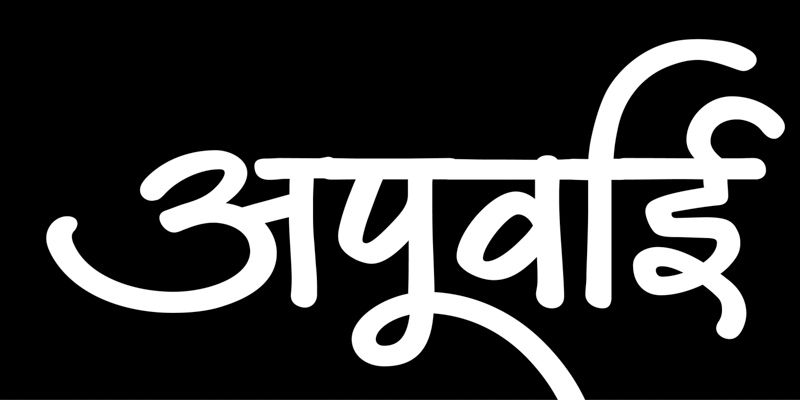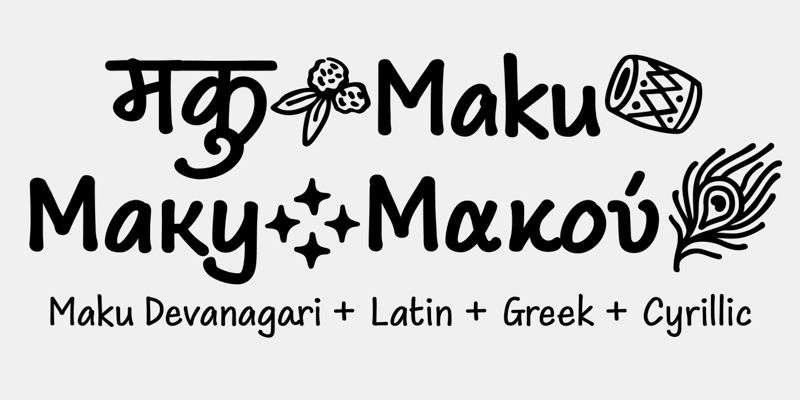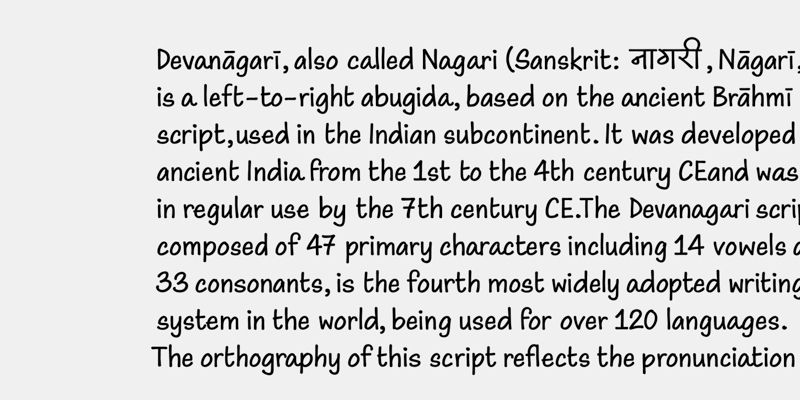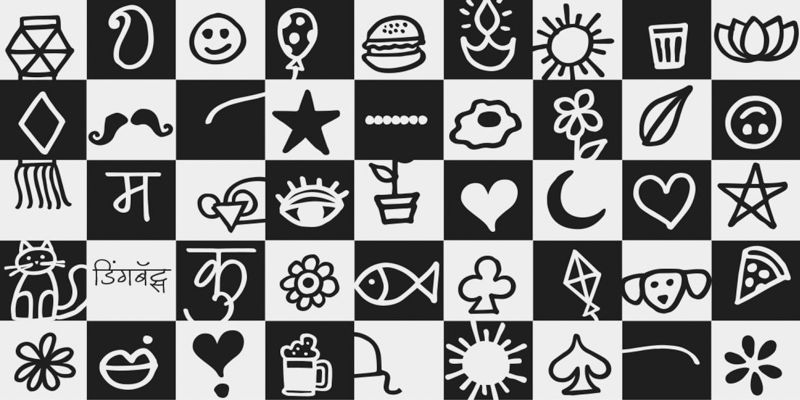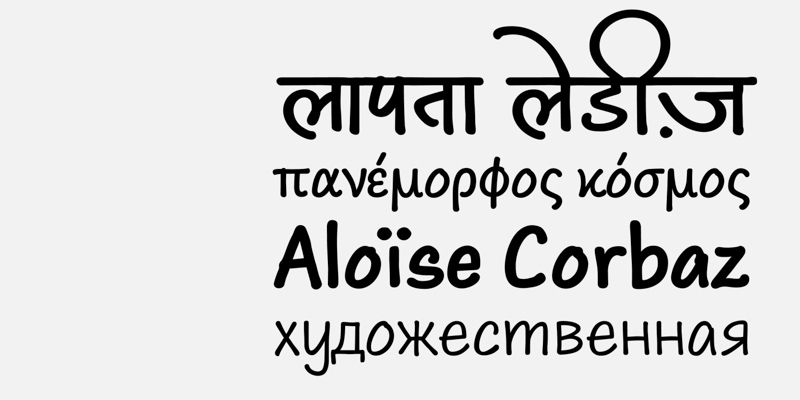
Maku apporte l’authenticité de l’écriture manuscrite à la typographie numérique grâce à ses caractères vivants, inspirés des écritures latine, devangari, grecque et cyrillique. Grâce à une technologie de police avancée, chaque caractère apparaît unique, avec de multiples variantes de glyphes qui alternent automatiquement pour éliminer les répétitions et créer un rendu manuscrit naturel.
Pour les conceptions nécessitant une touche d’originalité, Maku Devangari propose des versions ornées de toutes les lettres principales, ainsi que des initiales et des finales spéciales pour les mots. La police comprend également une vaste collection de symboles et d’illustrations qui complètent son style expressif. Disponible en quatre épaisseurs, Maku apporte chaleur et charme artisanal à tous vos projets.